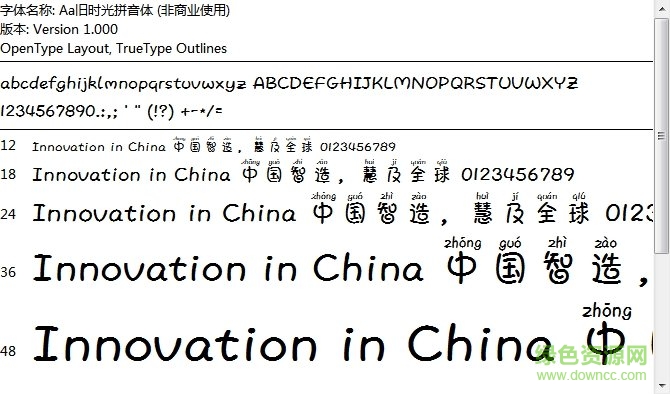
舊時光拼音體ttf是aa字體管家推出的一款非商業(yè)使用字體,字跡圓潤活潑,很有卡通字體的可愛和生動,讓你的文字閱讀更加舒適怡然,喜歡的朋友就來綠色資源網(wǎng)下載收藏吧!
P.S.拼音字體存在多音字拼寫錯誤的問題,多音字以常用音調(diào)為準(zhǔn)。
拼音字體都有相同的特色就是清晰醒目的拼音注釋,便于兒童對漫畫圖書內(nèi)容的獨立閱讀,也讓我們更好的讀書看報,而中英文的特色也決定了該字體的使用風(fēng)格,舊時光拼音體偏向于pop字體,用于海報創(chuàng)意或與兒童相關(guān)內(nèi)容的設(shè)計,效果更佳突出!